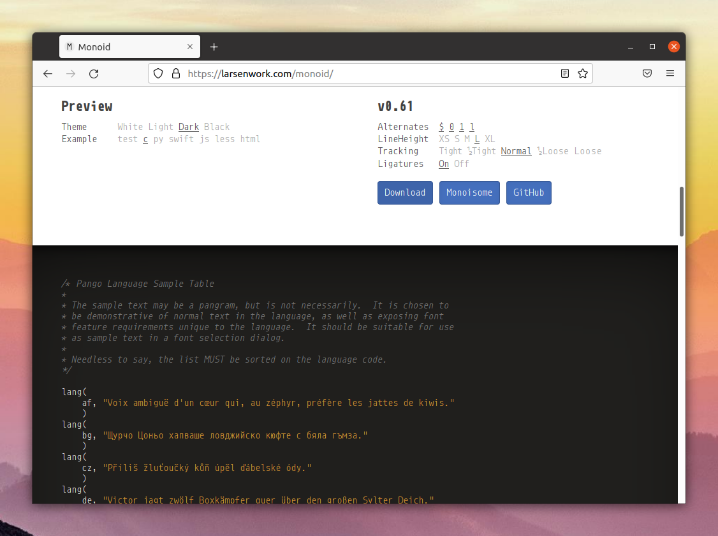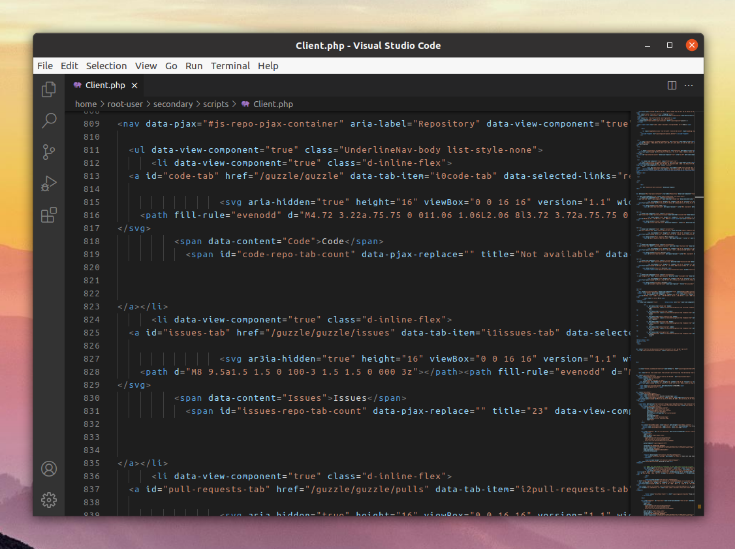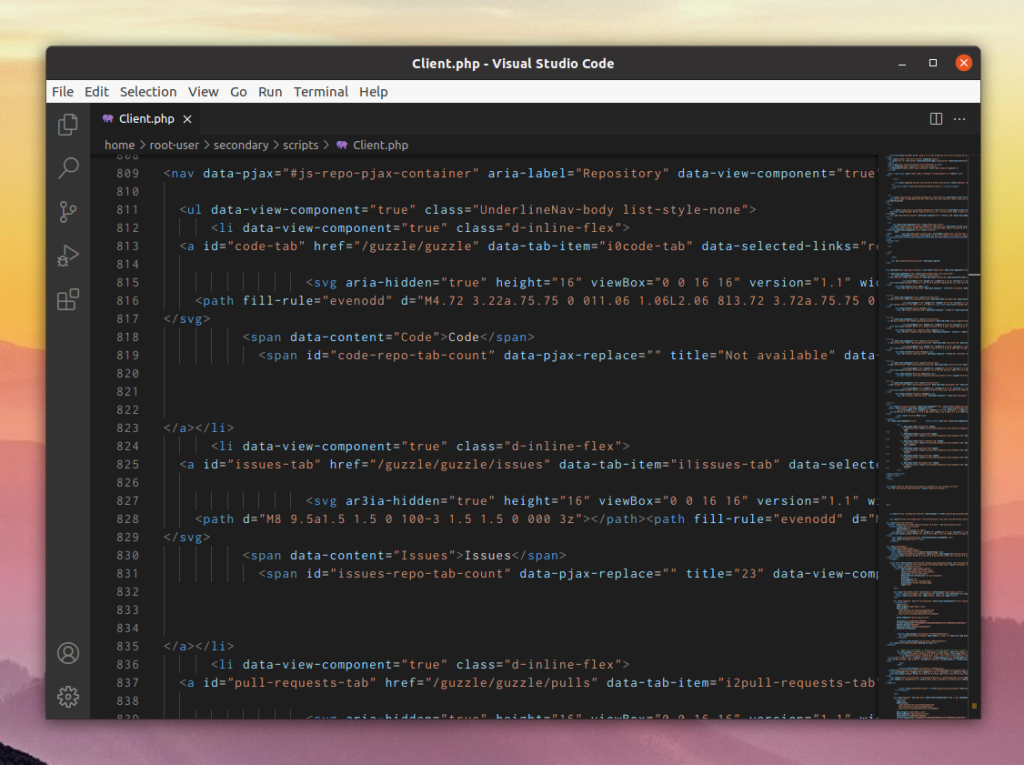
Во время работы с кодом программисту приходится подолгу сидеть за компьютером и смотреть на текст. Поэтому выбору шрифта стоит уделить особое внимание. Комфорт для глаз в этом аспекте стоит на первом месте. Но и визуальный стиль тоже стоит брать во внимание.
В рамках данной статьи мы расскажем, как должен выглядеть хороший шрифт для работы с кодом. А затем упомянем лучшие шрифты для программирования, их особенности и способы загрузки.
Лучшие шрифты для программирования
Читаемость – это один из важнейших параметров при выборе шрифта для работы с кодом. Все символы должны быть хорошо различимыми. А заодно иметь простую форму в едином стиле, чтобы глаза лишний раз не нагружались. Очень часто в них используются лигатуры. Это такие знаки, которые состоят сразу же из нескольких символов, сливающихся друг с другом. За счет такого подхода чтение становится более комфортным.
Но это далеко не все, что может упросить работу программиста. Мы подобрали 8 разноплановых шрифтов, каждый из которых имеет свои особенности. Ознакомьтесь с ними, выберите понравившийся и воспользуйтесь инструкцией по установке.
1. JetBrains Mono
Это бесплатный шрифт, который задумывался в первую очередь для разработчиков. Основной акцент в нем сделан на комфорт при чтении и редактировании кода. Все символы имеют схожую простую форму. У них одинаковая ширина и отсутствуют элементы на внешних границах, например, те же засечки. Это особенно удобно при вертикальном чтении.
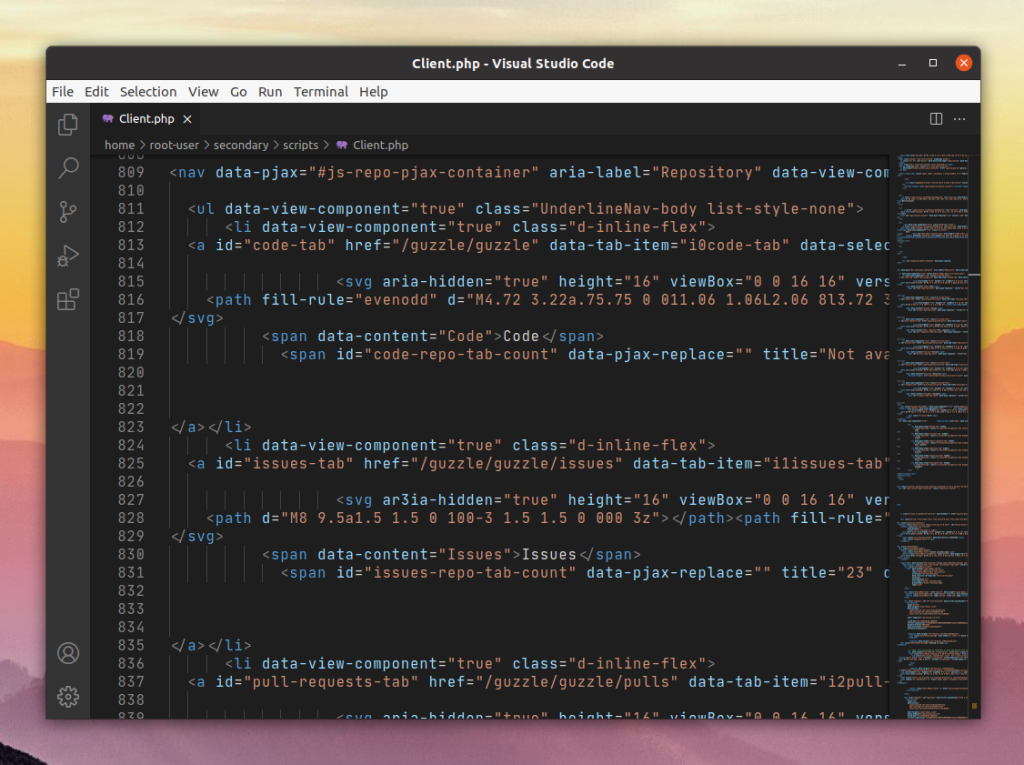
Давайте вкратце рассмотрим его особенности:
- Строчные буквы специально сделаны более высокими.
- У всех символов уникальный внешний вид, например, цифра 0 имеет точку внутри, а в случае с буквой O она отсутствует.
- Наличие лигатур.
- Курсив имеет нестандартный угол наклона в 9°.
2. Fira Code
Fira Code это вариация моноширинного Fira Mono. Начертание всех символов у них идентичное, но есть одно различие. Заключается оно в использовании лигатур, которые есть только в Fira Code. А сам шрифт изначально создавался для Firefox OS. Основной акцент дизайнер делал на лучшей читаемости.
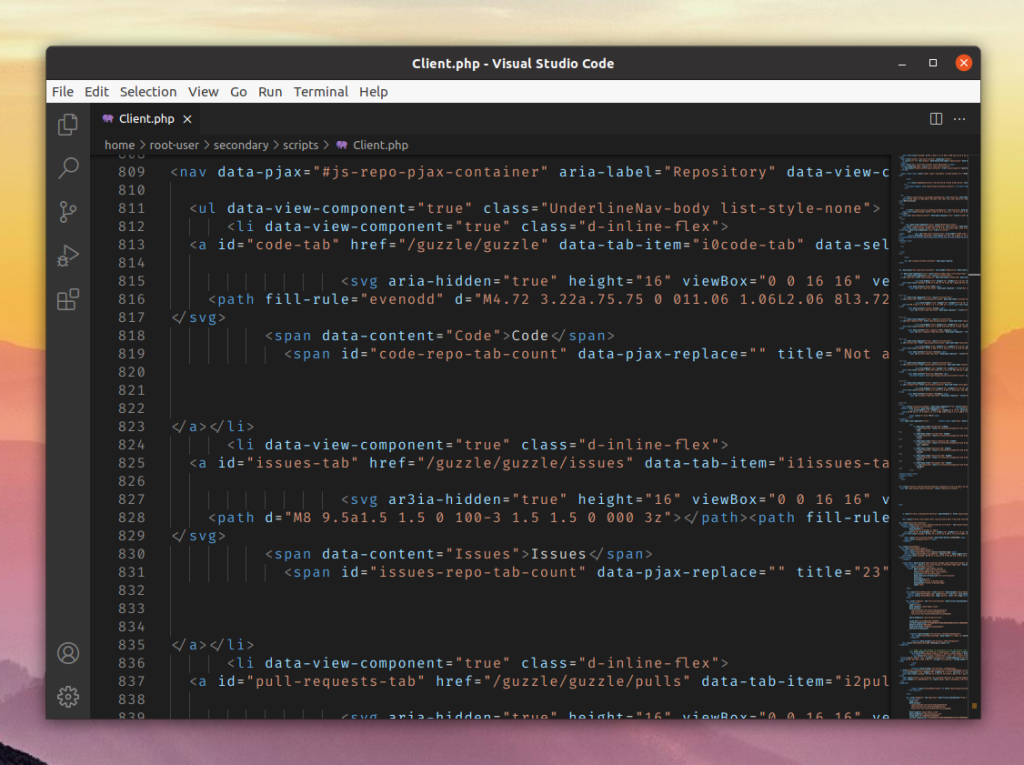
3. MonoLisa
Еще один моноширинный шрифт, задумывавшийся специально для разработчиков ПО. Помимо отличной читаемости, особое внимание создатели уделили визуальному стилю. Символы имеют увеличенную ширину, а по высоте могут незначительно отличаться. Присутствует 120 лигатур специально для программного кода. А у самих символов есть выбор альтернативного стиля.
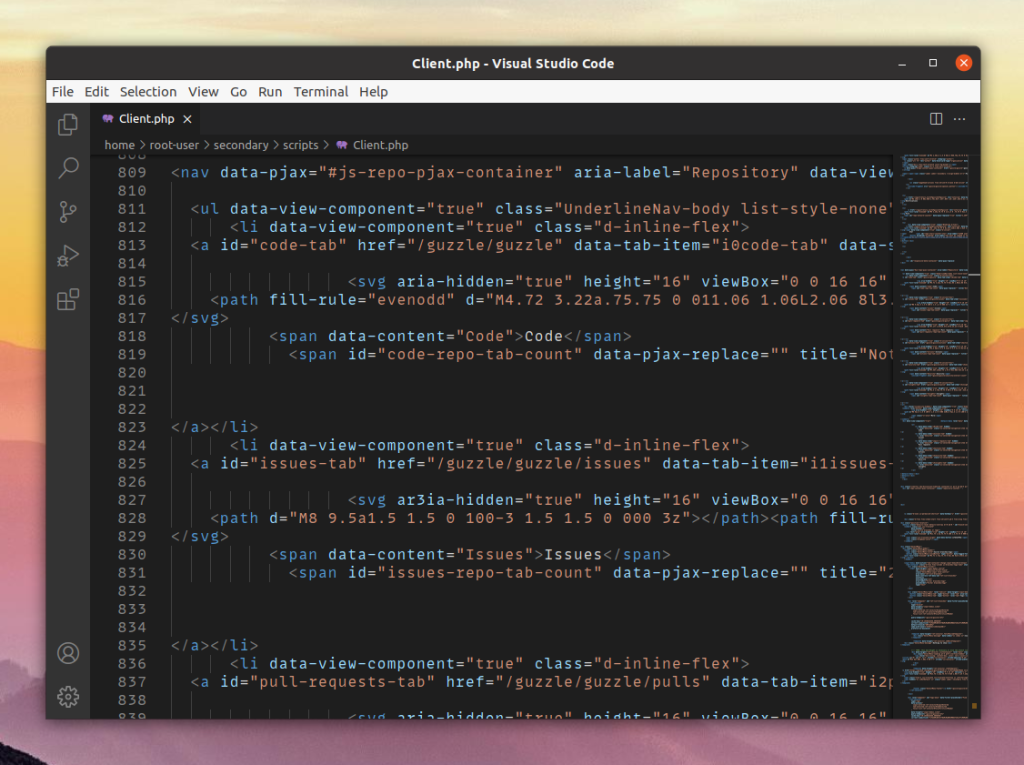
4. IBM Plex Mono
Основная задумка IBM Plex Mono – показать дух компании IBM и идеологию, прошедшую сквозь всю ее историю. По своему стилю это гротескный шрифт, который отлично читается на всех устройствах. Все описанное в сочетании с моноширинностью делает его оптимальным для работы с кодом.
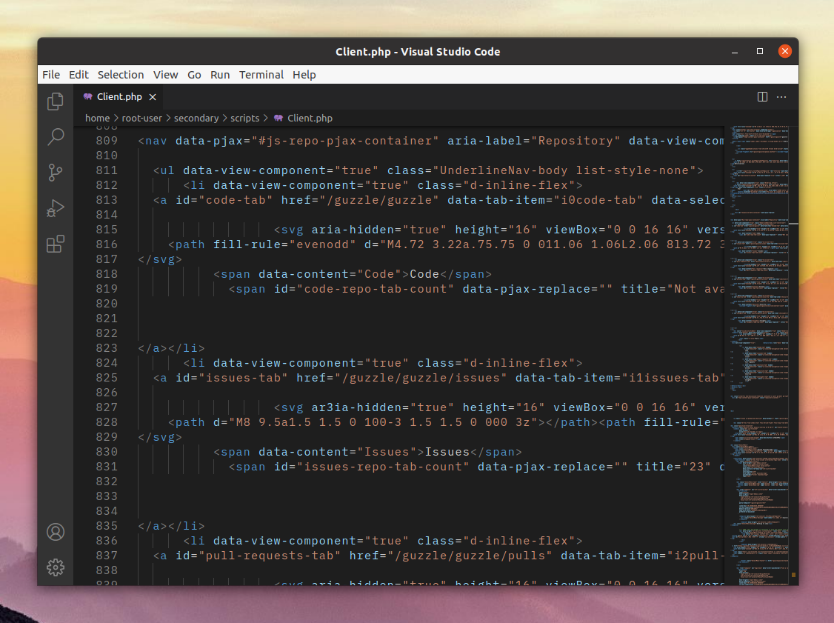
5. Source Code Pro
Даже по названию шрифта понятно, что он предназначается для чтения и редактирования исходного кода ПО. В качестве основы используется Source Sans. Из характерных особенностей можно выделить:
- Увеличенная высота и ширина символов, но между собой они сведены к одинаковым размерам.
- Символы не похожи друг на друга, что особенно важно, например, с i, l и 1.
- Увеличены размеры знаков пунктуации.
- Наличие набора глифов Adobe Latin 4.
- Поддержка множества языков, хотя в основном везде используется латиница.
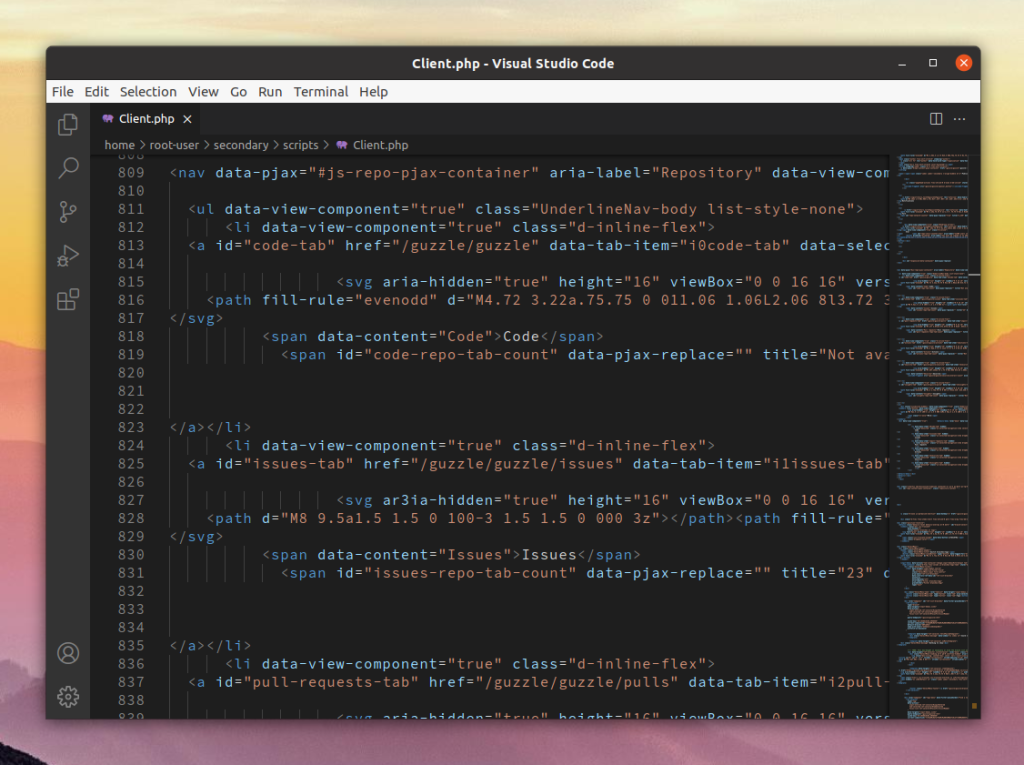
6. Monoid
Monoid по своему внешнему исполнению выполнен в пиксельном стиле. Шрифт отлично подходит для экранов с низким разрешением. Сами символы отлично различимы, имеют большие апертуры (вертикальные и горизонтальные срезы на границах). Особое внимание в нем уделено кастомизации, ведь многие параметры можно настроить еще до скачивания.